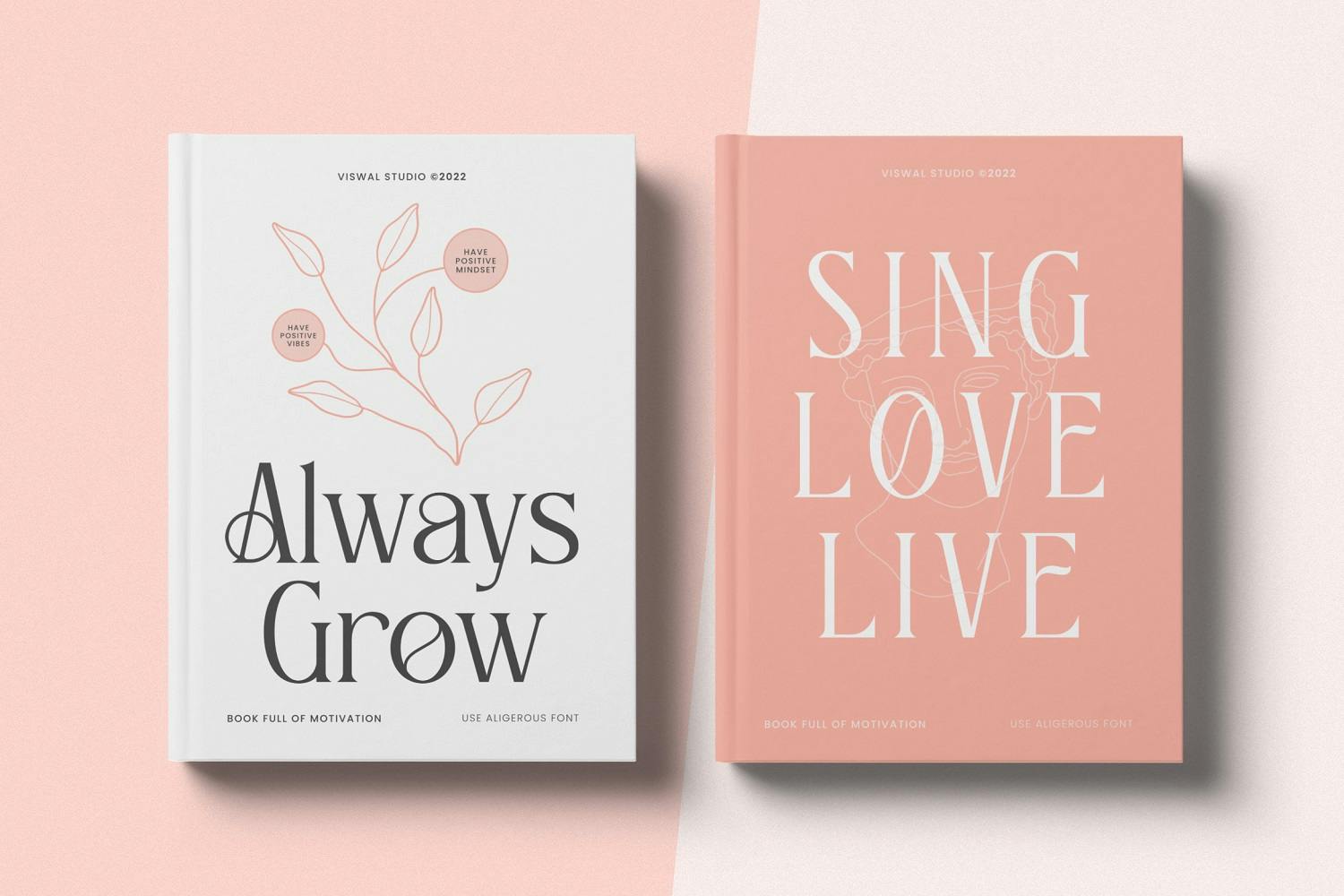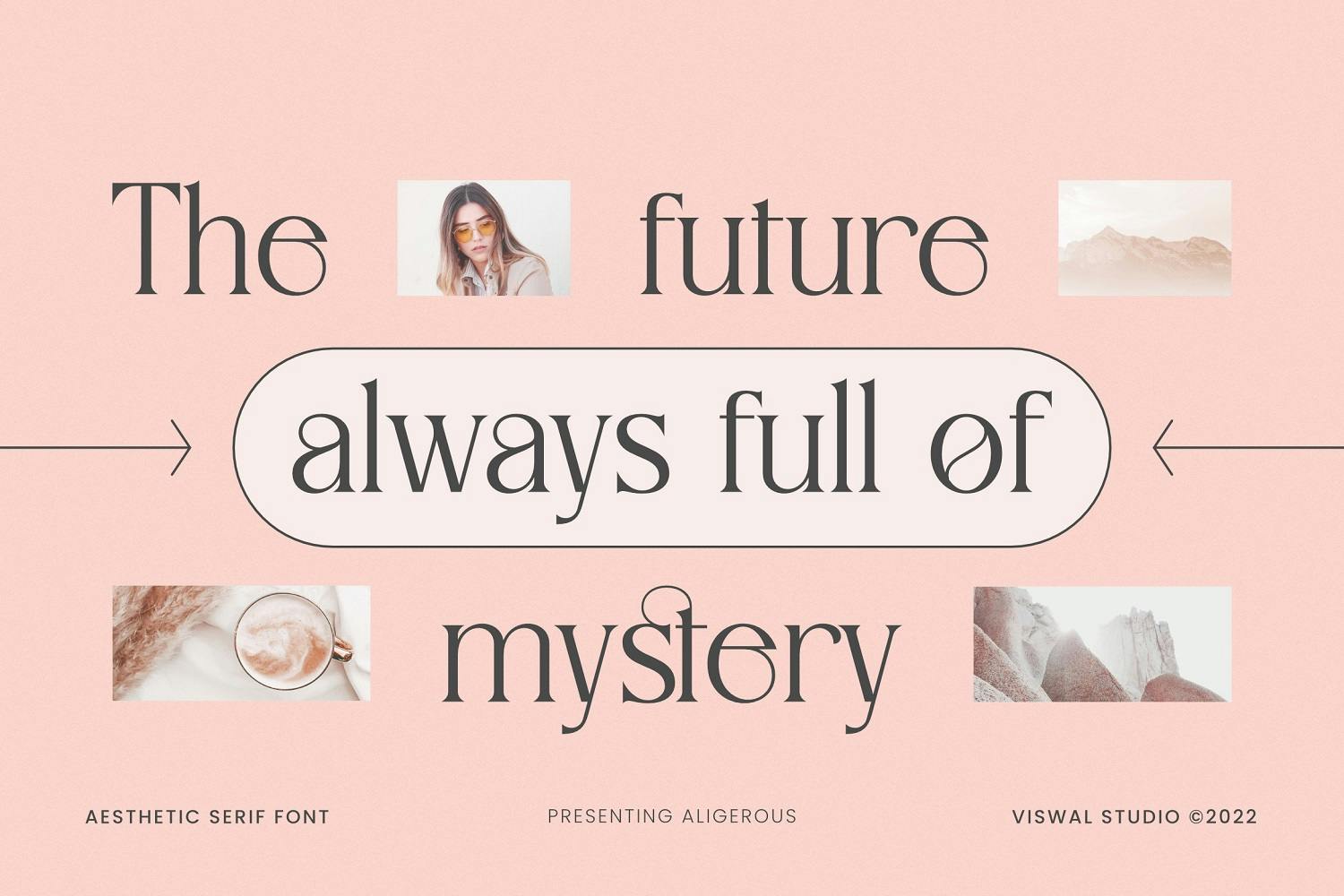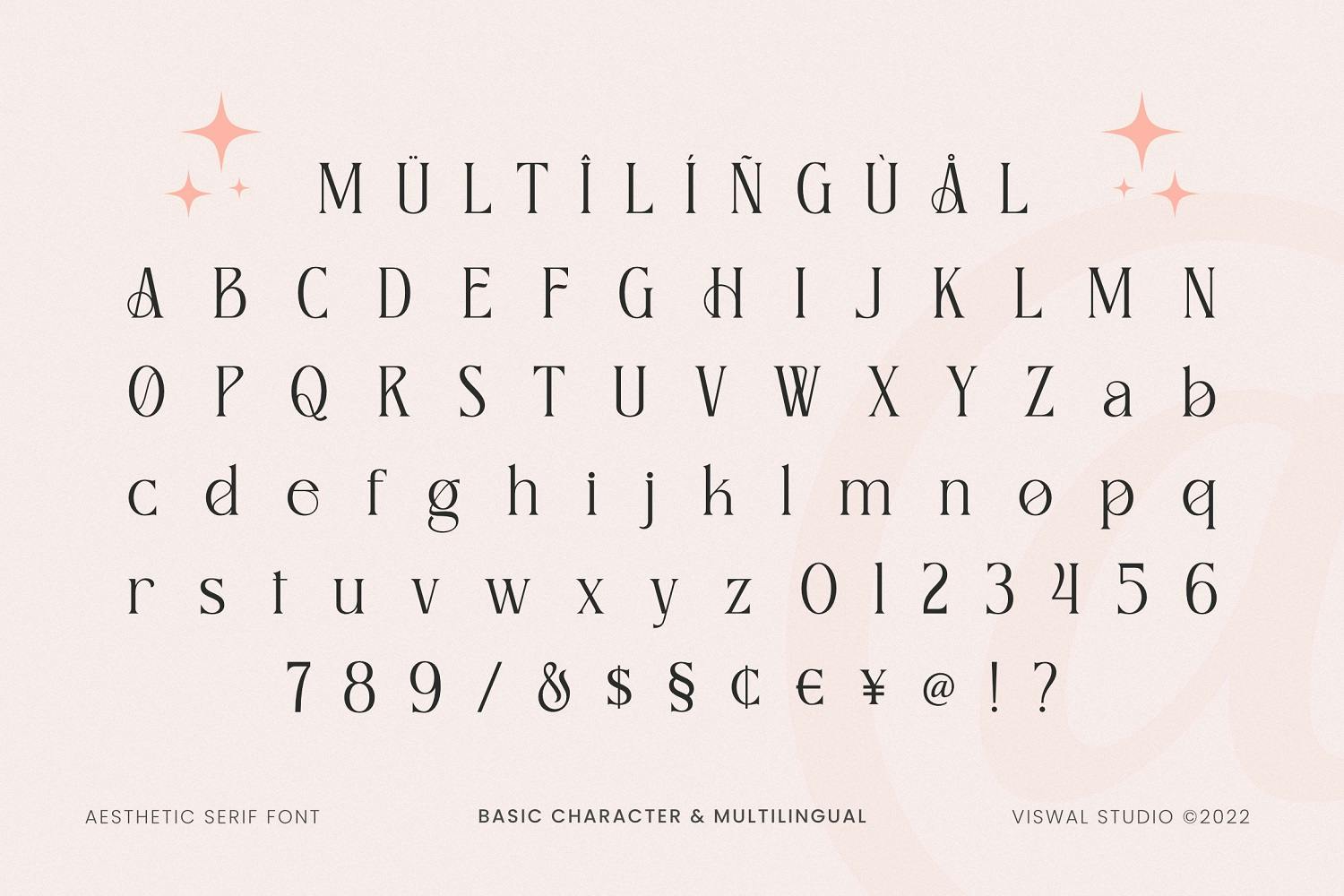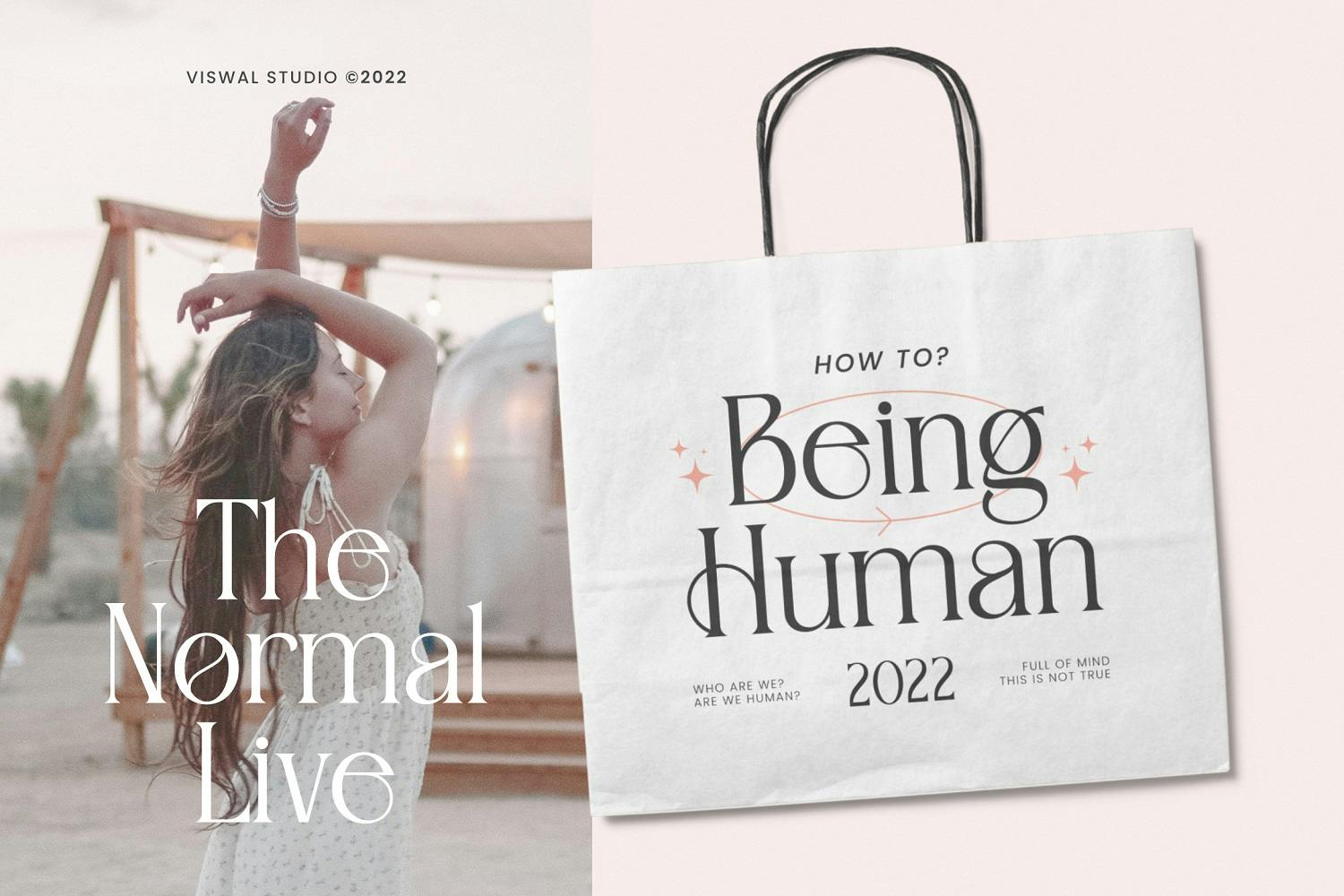
فونت مدرن Aligers را به شما معرفی میکنیم. این فونت مناسب برای طراحی لوگو، مجله، تبلیغات و برندینگ است. فونتهای ما شامل حروف بزرگ و کوچک، اعداد و نشانهگذاری، پشتیبانی چندزبانه و ویژگیهای OpenType میباشند. برای ایجاد طراحیهای شگفتانگیز، میتوانید این فونت را با سایر فونتها ترکیب کنید.